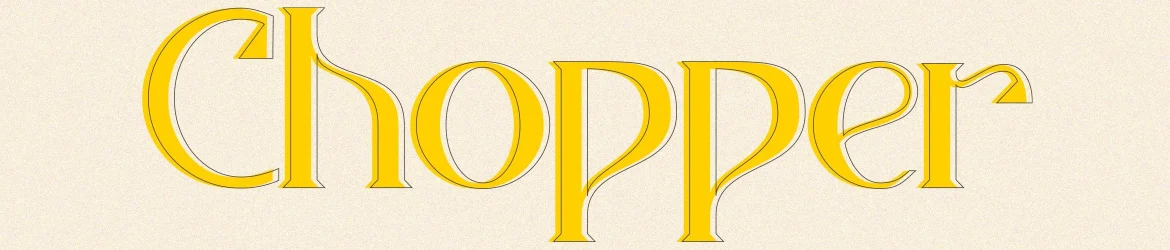
Chopper Font – Fonte Grátis
Chopper Font
A Chopper Serif é uma elegante e limpa fonte serif que se destaca na categoria de serif fonts. Seu design foi concebido em 2021 por MJ Type em Bandung, uma cidade vibrante no sul do Brasil conhecida pela sua rica cultura artística. Esta fonte apresenta belas curvas, tornando-a um ativo valioso para a biblioteca de fontes de qualquer projeto gráfico. A Chopper é ideal para headlines, criação de logotipos, design de adesivos e até mesmo cartões de visita, ajudando a enriquecer os seus projetos com um toque sofisticado e moderno. Não importa o tema do seu trabalho, a Chopper Serif Font certamente se encaixa perfeitamente, tornando-a uma excelente escolha para designers que buscam adicionar elegância às suas criações.